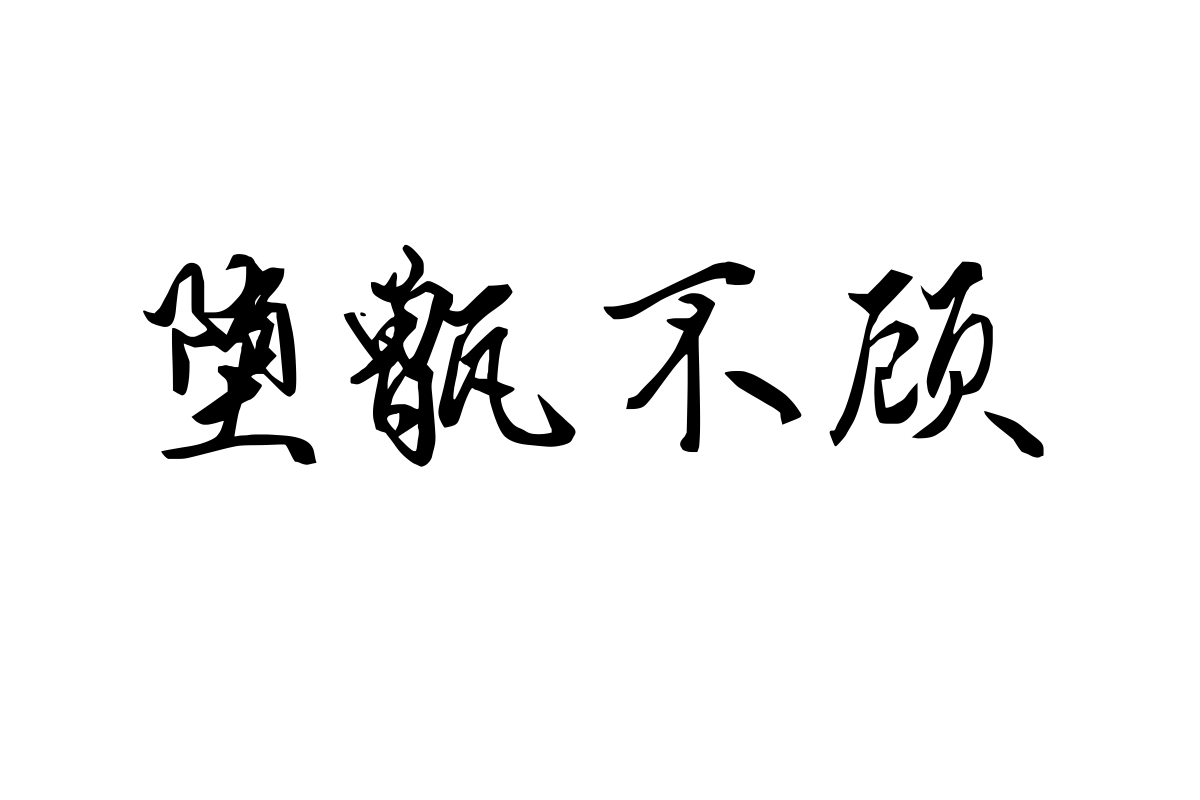
段宁软笔行书是一套由中国书法家段宁创作的书法字体。这套字体的特点是笔画流畅、结构自然,给人一种轻松愉悦的感觉。它适合用于各种需要书写的场景,如广告设计、产品包装、书籍封面等。
段宁软笔行书的笔画粗细适中,既有力度又不失柔美,使得整体视觉效果更加和谐。同时,它的字形结构也较为宽松,没有太多的拘束感,适合现代人的审美需求。
总的来说,段宁软笔行书是一款非常适合现代应用场景的书法字体,无论是在商业还是艺术领域都有着广泛的应用前景。